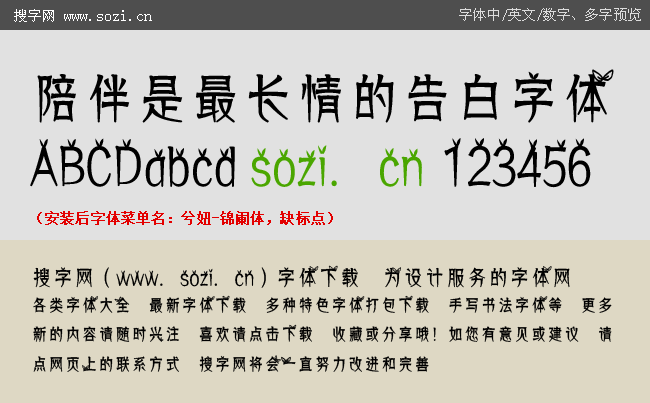
陪伴是最長情的告白字體
搜字網給大家提供一款陪伴是最長情的告白字體手機中文字體下載。這款手機字體是在方正懸針篆變簡體筆畫間插入了漂亮的卡通圖案。方正懸針篆變字體意在保留篆書韻味,同時將隸書與楷書筆畫特征熔于一爐,實為三種書體的統(tǒng)一。將傳統(tǒng)書法藝術與現代形式語匯融合,追求裝飾性及藝術美感,端莊秀美、開張疏朗,雍容大氣、復古卻易讀。加入了卡通圖案后又增添了趣味性,特別適合喜歡手機字體個性一些的朋友在手機上安裝使用。